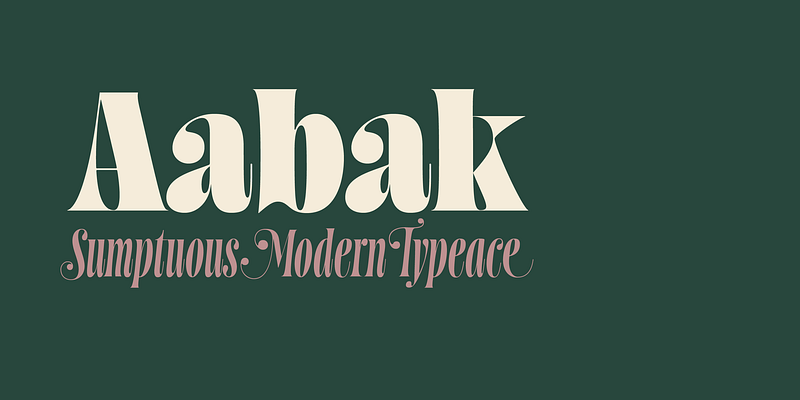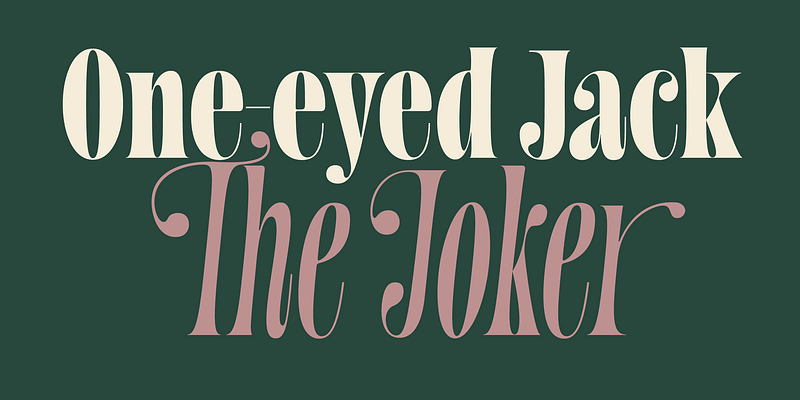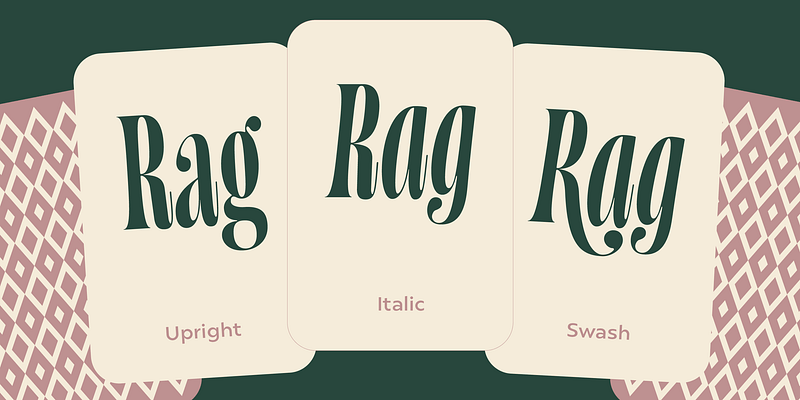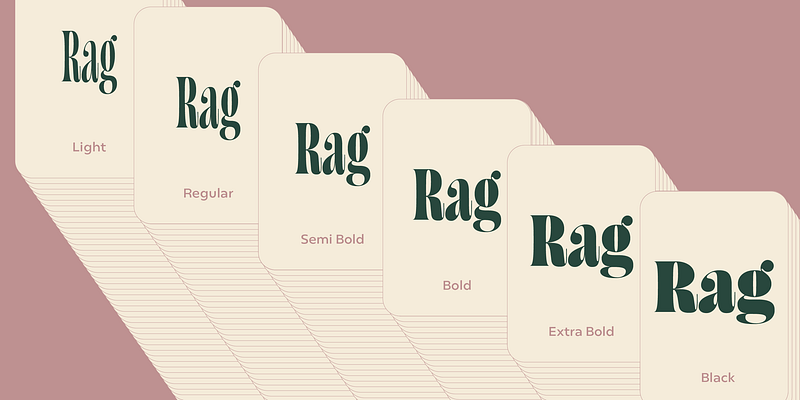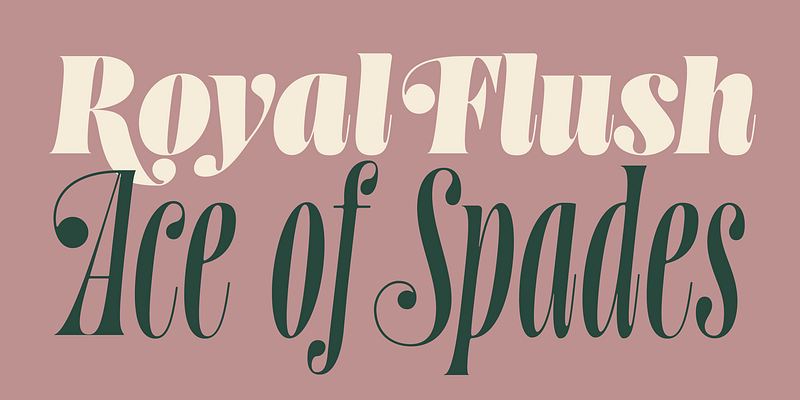
Aabak は、豪華なモダン書体ファミリーです。高コントラストで非常にエレガントなディドンのようなシェイプに、60 年代のサイケデリックなレタリングの流動性が少し加わり、新鮮さを叫ぶ現代的な書体が生まれました。ブランディング、広告、見出し、ポスター、映画のタイトルなどに最適です。
このデザインは、圧縮されたパンチの効いた外観を実現するために、意図的に多くの空白を破壊しています。涙滴型の終端と溶けていくようなセリフが、驚くほど見事な組み合わせを生み出しています。
シャープな結合部は平滑化され、温かみのある繊細な感覚を伝えています。
Aabak は合計 18 のスタイル、6 つのウエイト、3 つの異なるカット (アップライト、イタリック、スワッシュ) で構成されています。スワッシュスタイルには、さらに豊かな感触を与えるターミナルフォーム機能もあります。